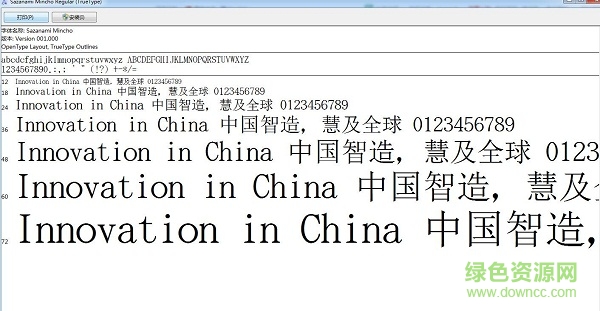
さざなみ明朝字體是一款和中文的宋體非常像的日文字體,優(yōu)雅挺拔,實用性強,非常適合顯示大量文字,可用于Word、PPT等軟件中的文章排版,有需要者歡迎免費下載!
宋體字在明朝時傳入日本,因而日本稱之為“明體”或“明朝體”,后來傳入韓國、中國臺灣,所以兩地也有明朝體的叫法。時至今日,由于中日兩國文字簡化方案的不同,兩國文字已經有了很大的不同,明朝體也就徹底成為一種外文字體了。
宋體字進一步發(fā)展,康熙中期以后逐漸形成清代的風格。最明顯的特征在于此時的宋體字字形比明末清初更方正,更接近于后來我們熟悉的印刷體。到乾隆時期,宋體字已大體定型,其橫畫收筆的三角、豎畫起筆的三角等,與現(xiàn)代宋體字基本相同。